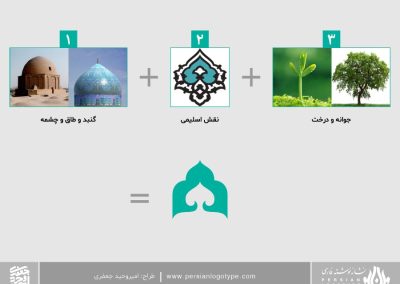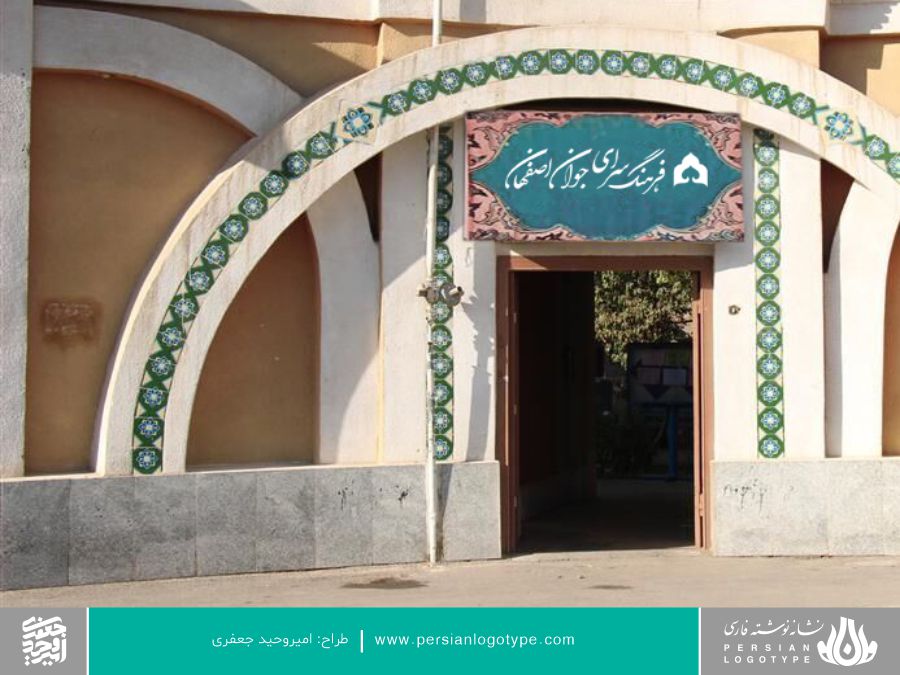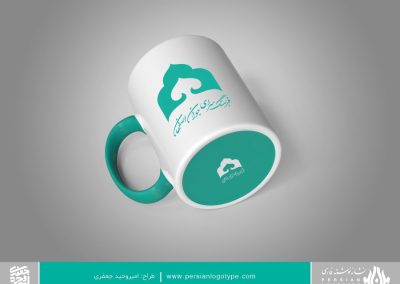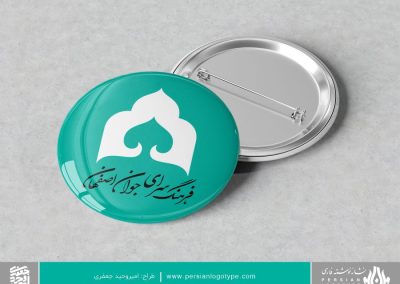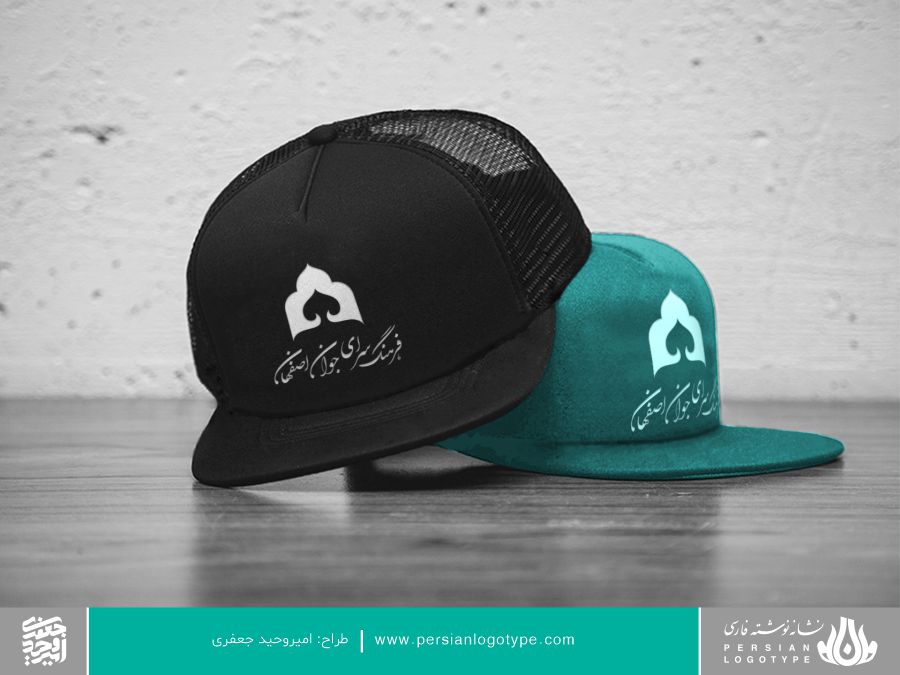
طراحی لوگو فرهنگسرای جوان اصفهان (طرح پیشنهادی1)
در طراحی این لوگو، استفاده از نمادها و المانهایی که نشان دهنده فرهنگ و هویت ایرانیست در کنار به نمایش گذاشتن هدف مجموعه فعالیتهای فرهنگسرای جوان اصفهان که بر رشد و پرورش نهال جوانان همت دارد، محور قرار گرفته است که شرح آنها چنین است:
1-فرم گنبد، قوسهای گنبدی شکل یا طاق و چشمه
گنبد:
گنبد، یک عنصر مهم در معماری سنتی ایران و به ویژه اصفهان است که در بسیاری از بناهای تاریخی و مذهبی این شهر دیده میشود. گنبد، نشاندهنده عظمت، زیبایی، و ارزش فرهنگی این شهر است که در طول تاریخ، پایتخت و مرکز هنر و علم بوده است.
طاق و چشمه:
طاق و چشمه دو عنصر مهم و مشهور در معماری ایرانی هستند که در بسیاری از بناهای تاریخی و زیبای این کشور دیده میشوند. این دو عنصر، هم از لحاظ سازهای و هم از لحاظ زیباییشناسی، اهمیت ویژهای دارند. طاق و چشمه در بناهای مختلفی در ایران مانند مسجد، مدرسه، باغ، کاروانسرا، آبانبار، پل، بند، باغ، حمام، تکیه، گورستان و غیره به کار رفته است.
2-نقوش اسلیمی:
نقش اسلیمی، یکی از نقوش انتزاعی گیاهی است که در هنر ایرانی، بسیار مورد استفاده قرار میگیرد. نقش اسلیمی، نشاندهنده زیبایی، هنر، و خلاقیت ایرانی است که در هنرهای مختلف ایران مانند معماری، نقاشی، صفحهآرایی، گلیمبافی، و غیره دیده میشود.
3-جوانه و درخت:
جوانه و درخت، عناصری هستند که در طبیعت، نماد رشد، زندگی، باروری، و تکامل هستند. در واقع فرم جوانه و درختی که برگرفته از نقوش اسلیمی است و در دل سرایی عالی و ساخته شده بر پایه معماری ایرانیست، نشاندهنده آن است که در فرهنگسرای جوان اصفهان، جوانان مسیر رشد و تکامل خود را بر پایه فرهنگ و هویت اصیل خود، طی خواهند کرد.
رنگ لوگو
رنگ سبز نماد طبیعت، رشد و زندگی، تجدید حیات است در دین اسلام نیز سبز رنگ پیامبر اسلام و خاندان مطهر او است و نشاندهنده قیام و تجدید حیات است. رنگ آبی نماد آسمان، دریا، سفر درونی، درک عمیق، روح، تقوا، صداقت، حکمت، ایمان، حقیقت و بهشت است. این رنگ همچنین با تفکر، دعا، عرفان، روحانیت، و معنویت نیز ارتباط دارد.
رنگ فیروزه ای که از ترکیب این دو رنگ ذکر شده به دست می آید، خصوصیات آن ها را نیز دارد و آن را در گنبدهای شهر اصفهان به وضوح خواهیم دید.